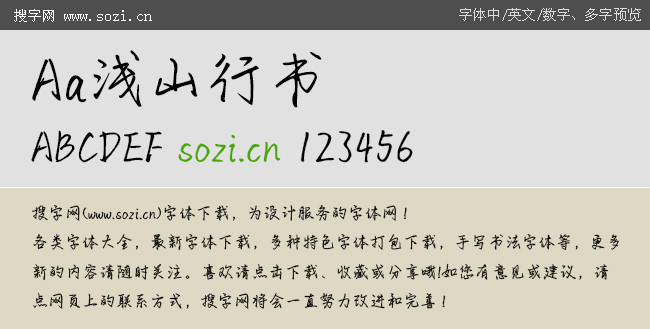
Aa淺山行書(shū)字體
搜字網(wǎng)給大家提供一款A(yù)a淺山行書(shū)字體中文字體下載,這是一款手寫(xiě)風(fēng)格的書(shū)法字體,字體書(shū)寫(xiě)自如,效果瀟灑大方,適合海報(bào)設(shè)計(jì)、包裝畫(huà)冊(cè)等宣傳廣告等應(yīng)用(此字體為個(gè)人非商用版,如需商用請(qǐng)聯(lián)系作者購(gòu)買(mǎi)版權(quán))。